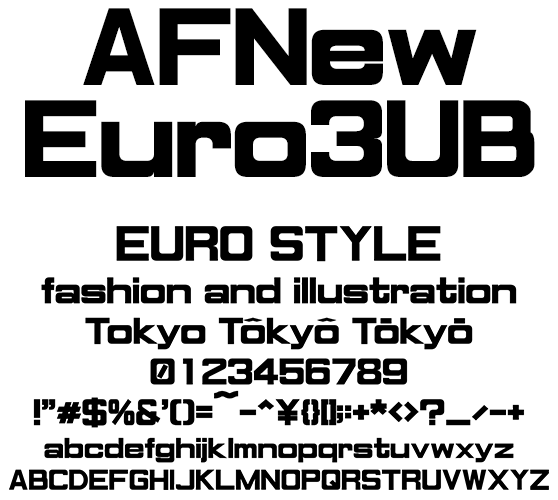
ユーロスタイル欧文 AFNewEuro3UB
AFNewEuro3UB
[AFNewEuroEB2.ttf]のウエイトを太く、扁平を加え少々のデザイン変更とカーニング調整しました。1960年代に見られたEuro style Fontを再現、ベースは古風でありながらも洗礼されたデザイン、コンテンポラリーファッションに最適です。